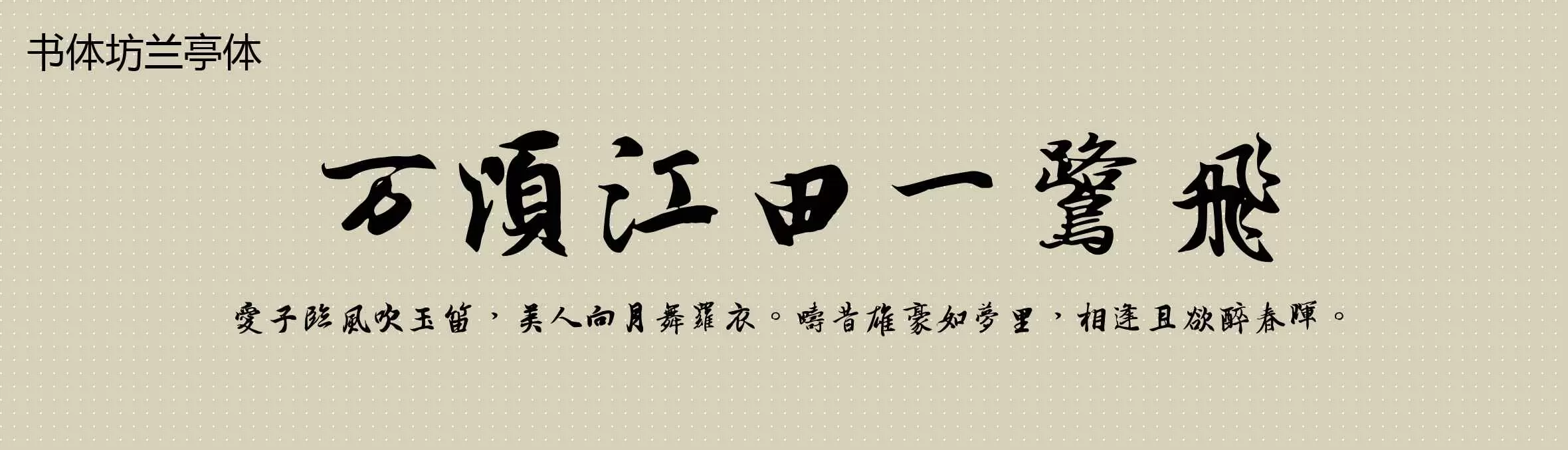
书体坊兰亭体是一种独特的中文书法字体,由中国著名书法家王羲之所创。这种字体以其流畅的书写风格和高雅的艺术感受而著称。书体坊兰亭体是中国传统书法艺术的代表之一,被广泛应用于印章、广告牌匾、书法字画等领域。它的独特之处在于其不仅仅是一种字体,更是一种文化与艺术的传承和表达。它的创作历史悠久,经过多年的发展和演变,如今已经成为世界范围内广为使用的书法字体之一。